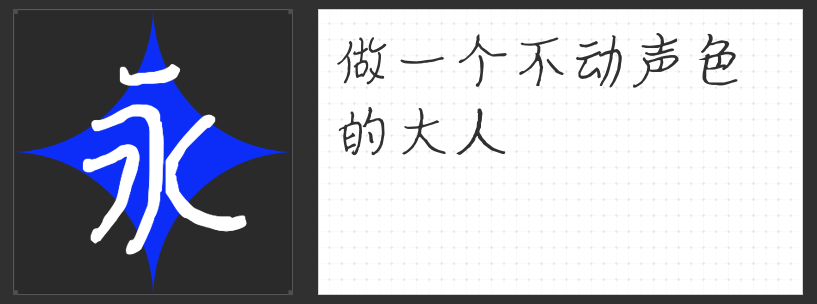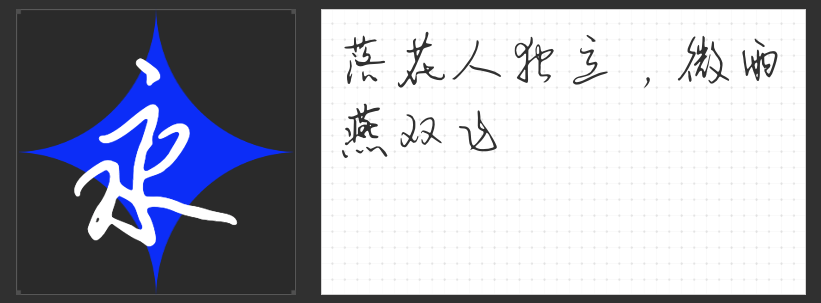
Vlog设计进阶指南:四款高辨识度字体的美学赋能
在短视频内容同质化的今天,视觉设计的独特性成为吸引观众的关键。一款契合主题的字体不仅能强化信息传递,更能塑造独特的品牌调性。以下四款兼具设计感与实用性的字体,将为你的Vlog注入专业级视觉灵魂。
一、字青春悸动简 常规
这款字体以均衡的结构与清晰的笔画构建出视觉舒适区,既保留了传统书法的优雅韵律,又通过现代设计手法强化了可读性。其清秀别致的风格在快节奏的短视频中形成视觉缓冲,无论是标题字幕还是信息标注,都能以克制的美感平衡画面元素。特别适合知识分享、生活记录等需要营造清新氛围的Vlog类型。
二、励字造仲夏简 常规
将传统碑刻的坚挺骨力与手写笔触的灵动自由巧妙融合,这款字体通过斑驳边缘与洒脱钩笔传递出独特的艺术张力。坚挺的竖画与随性的连笔形成视觉对话,既适用于商业类Vlog的标题强化,也能为文艺向内容增添人文厚度。其多场景适配性源于对传统与现代审美的精准把握,让每个文字都成为讲述故事的视觉符号。
三、安景臣硬笔行书
突破字库字体常见的机械感,这款以签字笔书写的行书字体通过笔锋的虚实转换构建出流动的韵律。每个字符都像独立的舞蹈动作,组合后形成连贯的视觉叙事。在MV字幕或品牌宣言等需要情感张力的场景中,其变化多端的笔画结构能自然引导观众视线,创造出独特的沉浸式阅读体验。
四、MyFont濑户风车简
略带弧度的笔画与圆润的转折设计,赋予这款手写体天然的亲和力。不追求几何意义上的精准,却通过微妙的倾斜角度与笔画粗细变化传递出孩童般的纯真感。在宠物、亲子或美食类Vlog中,这种充满温度的字体能瞬间拉近与观众的距离,让信息传递更具情感共鸣。
当精心剪辑的画面遇上恰到好处的字体设计,视觉语言的完整性将得到质的提升。这四款字体各具美学特质,既能独立支撑特定风格的视觉体系,也可通过组合搭配创造丰富的视觉层次,为Vlog内容赋予更持久的记忆点。